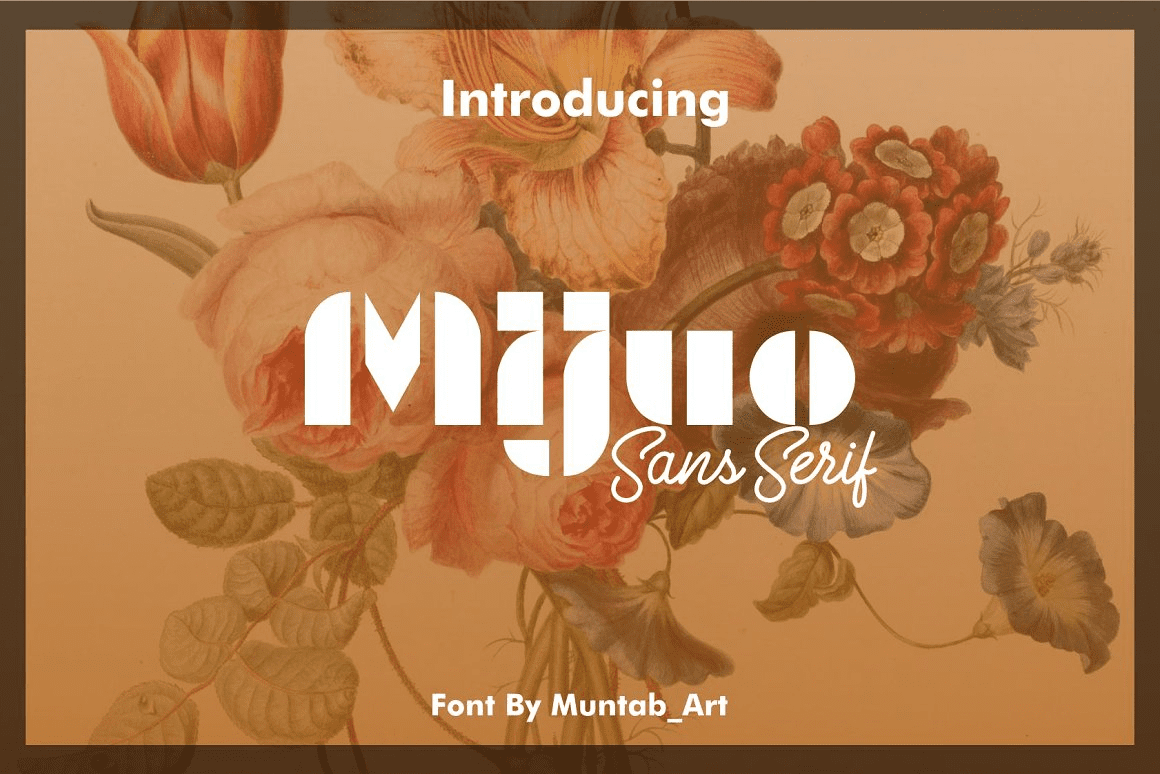
Название: Mijuo - Modern Font
Шрифты миджуо включают в себя заглавные буквы, цифры, большой диапазон знаков препинания.
Шрифт Сан-Сериф с современным стилем.
Создан для плаката, веб-дизайна, брендинга, иллюстраций, значков и некоторых других работ.
Название: Mijuo - Modern Font
Шрифты миджуо включают в себя заглавные буквы, цифры, большой диапазон знаков препинания.
Шрифт Сан-Сериф с современным стилем.
Создан для плаката, веб-дизайна, брендинга, иллюстраций, значков и некоторых других работ.